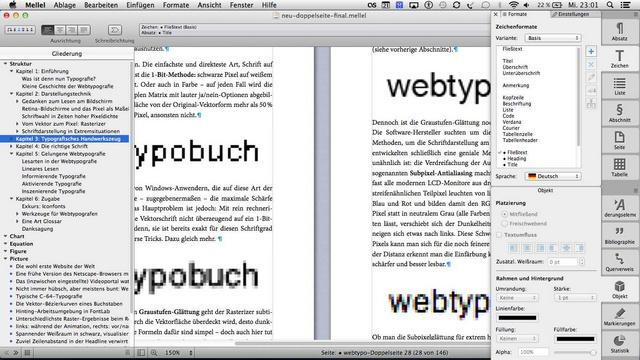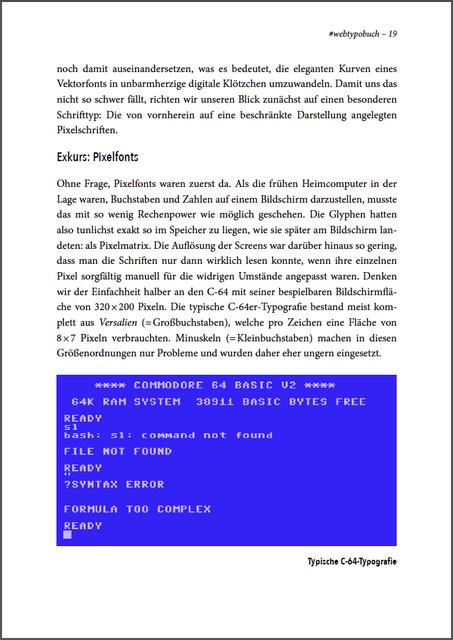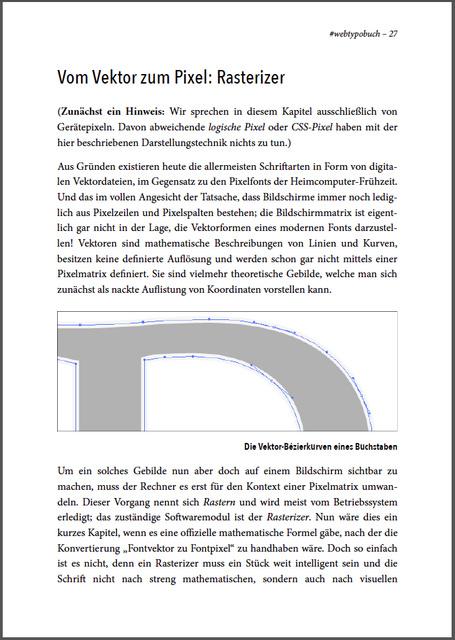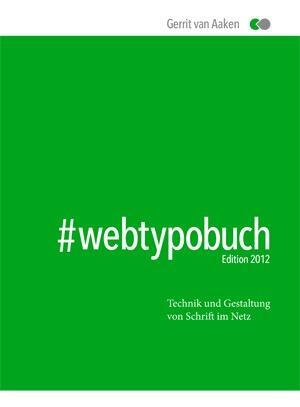
Das Internet verleiht jedem eine Stimme. Jeder darf bloggen, twittern und kommentieren. Doch die Anzahl derer, die in einem bestimmten Fachbereich wirklich etwas zu sagen haben, ist meistens überschaubar und daher fallen diese Personen besonders auf. Wenn die Themen Webdesign und Typografie zusammentreffen, ist Gerrit van Aaaken solch eine Person an der man nicht vorbeikommt.
Ein deutscher Blogger der ersten Stunde, der auf seiner Seite Praegnanz.de mit kleinen typografischen Essays schon früh auf sich aufmerksam machte. Sein gesammeltes Webtypografie-Wissen hat er nun in einem Buch zusammengefasst.
Zum Inhalt: Das Buch beginnt mit einer kurzer Einführung zu Typografie im Allgemeinen und Webtypografie im Speziellen. Dann steigt van Aaken im zweiten Kapitel bereits ausführlich in die Problematiken der Webdarstellung ein, insbesondere die pixelbasierte Darstellung im Web und wie sie mit den Ausgabegeräten und Schriftdarstellungen unter unterschiedlichsten Bedingungen zusammenhängt.
Im dritten Kapitel wird ausschnittshaft verschiedenes Handwerkszeug zu Schrift im Netz vermittelt – etwa der Umgang mit Sonderzeichen, Abständen, Kontrasten, Silbentrennung und ähnliches.
Bis hierhin lässt sich die Zielgruppe noch nicht so ganz klar definieren. Manche Details werden für Einsteiger kaum verständlich sein, weil sie ohne nähere Erklärung zu speziell sind oder zu weit in der Vergangenheit liegen. Andere Dinge, die den meisten Grafik- oder Webdesignern vertraut sein dürften, werden dann aber sehr ausführlich erläutert.
Richtig in Fahrt kommt das Buch dann aber ab Kapitel 4 wenn es um die Webtypografie heute geht. Im Kapitel »Die richtige Schrift« werden Schriftwahl und die heute schon schier unüberschaubaren Möglichkeiten der Webfont-Einbindung ausführlich und vor allem auch praxisnah beleuchtet. In Kapitel 5 geht es dann mit »gelungener Webtypografie« weiter. Über eine Klassifikation von Textarten im Webdesign wird anhand von Praxisbeispielen deren optimaler Einsatz erklärt.
Wer im Webdesign arbeitet ist es gewöhnt, sein Wissen nicht in dauerhaft gültigen Hardcover-Büchern finden zu können. Man muss ständig am Ball bleiben und sich überall im Netz informieren – die guten Fachartikel sind dabei meist in Englisch und was heute der Stand der Technik ist, stimmt 2 Jahren vielleicht schon nicht mehr. So halten sich oft auch Fehler und Notlösungen länger, als dies eigentlich der Fall sein müsste. Fundiertes deutsches Wissen, dass zusammenhängend erklärt wird, ist in diesem Fachgebiet daher äußerst selten und schon deshalb sticht das#webtypobuch positiv heraus. Wer als Grafik- oder Webdesigner ein Grundverständnis von Webdesign und Typografie hat, kann sich in diesem Buch auf den neuesten Stand bringen und eventuelle Wissenslücken füllen.
Das Werk ist dabei übrigens aber eher ein »Verstehbuch« als ein ausführliches Lehrbuch. Konkrete Code-Beispiel, wie etwa die Einbindung von Webfonts nun funktioniert und was es im Detail alles zu beachten gibt, finden sich in diesem Buch eher nicht. Das Buch bereitet hier nur eine inhaltliche Basis.
Damit das Buch ePub-tauglich und damit auf verschiedensten Geräten darstellbar ist, wurde es als reiner Fließtext im Textverarbeitungsprogramm Mellel entworfen. Eine klassische Gestaltung von Einzelseiten konnte somit nicht erfolgen. So ist das Buch also auch selbst ein Spiegelbild der heutigen technischen Möglichkeiten und Beschränkungen. Ein Buch über Typografie, das gestalterisch hinter den Ansprüchen zurückbleibt, die wir uns in den letzten 500 Jahren Druckgeschichte erarbeitet haben – weil es die heute Technik elektronischer Bücher aktuell nicht besser hergibt.
Mit einem Preis von knapp 10 Euro für circa 150 Seiten (gemessen am PDF) und der Möglichkeit des Probelesens im Internet kann man mit dem #webtypobuch nicht viel falsch machen. Der lockere und persönliche Schreibstil gefällt und wirkt selbst auch wie eine Folge von zusammengehörigen Blog-Beiträgen vonPraegnanz.de. Für ein Werk, das sich mit den normalen gedruckten Fachbüchern in diesem Bereich messen kann, reicht es in Tiefe und didaktischer Aufbereitung dann aber nicht ganz aus. Daher von mir ein Sternchen Abzug, ansonsten aber einen Glückwunsch zum gelungenen Erstlingswerk!
Untertitel: Technik und Gestaltung von Schrift im Netz